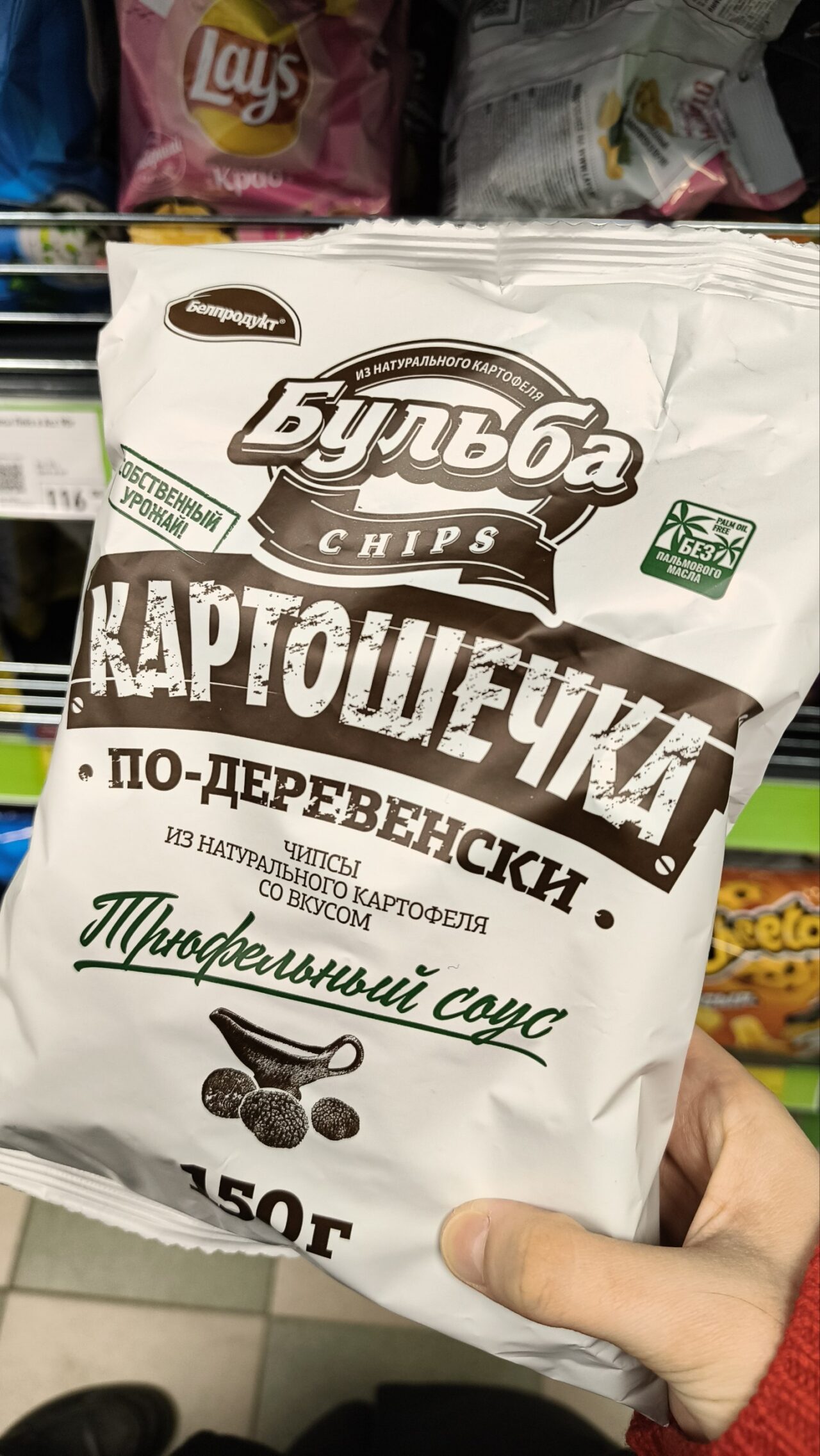
Mojito — живой и бодрый каллиграфический шрифт на основе письма круглой кистью (брашпеном).
Автор тщательно переосмыслил форму всех знаков и нарисовал очень лаконичный, точный и чистый контур, который будет прекрасно выглядеть при любом увеличении. В Mojito около 1400 знаков, в том числе альтернативы, лигатуры, начальные и конечные формы.Благодаря этому буквы не повторяются, а их сочетания выглядят максимально естественным образом, особенно в кириллице. При наборе одними прописными буквами в Mojito можно включить замену основных форм знаков на упрощённые, спроектированные специально для этой цели. Два дополнительных начертания имитируют письмо по шероховатой поверхности и оттиск высокой печати. Mojito прекрасно подойдёт для упаковки и рекламы, продуктов и напитков, кафе и ресторанов, крафтовых и рукодельных вещей, детских книг, журналов и т.д.
Шрифт спроектирован Захаром Ящиным и выпущен компанией Паратайп в 2017 году. Дополнительные начертания подготовлены Александром Любовенко.
Короткая история создания шрифта от ПараТайпа:
Всё началось чуть более года назад вот с этих набросков — очередной задумки Захара Ящина.
Надо сказать, что зерно упало в подготовленную почву — мы планировали расширение библиотеки умными рукописными шрифтами, имитирующими реальное письмо различными инструментами. Так что, довольно быстро появились первые оцифрованные варианты, а с ними — проявился характер шрифта.
Довольно быстро всем, включая автора, захотелось большей динамики и, как следствие, дополнительной связности форм.
Следом, стали необходимы начальные и конечные формы, контекстуальные альтернативы, лигатуры, — т.е., всё, что делает шрифт живым и естественным. Свойства шрифта (OpenType features) сформировались так, чтобы максимально упростить работу в приложениях и, там где это возможно, контекстуальные альтернативы и позиционные формы подставляются по умолчанию.
Вот как автор сам оценивает полученный результат:
Шрифт Мохито – это соединенный рукописный шрифт, имитирующий написание остроконечной кистью. Нарисован З.Ящиным по заказу фирмы ПараТайп. Шрифт Мохито должен как можно аутентичнее воспроизводить скорость и экспрессию ручного написания, при этом нивелируя случайные огрехи написания от чересчур сильного сопротивления материала, добавляя аккуратность и упорядоченность. Многие существующие рукописные шрифты грешат излишней механистичностью. Шрифт Мохито старается совместить тепло руки каллиграфа с холодной строгостью типографики. Нейтральный и динамичный рисунок букв делает шрифт универсальным в применении: и в виде заголовка в журнале, и в фирменном стиле, и на этикетке в магазине, и на футболке с рисунком.
Галерея изображений шрифта Мохито\Mojito:
Шрифт Мохито\Mojito в жизни: